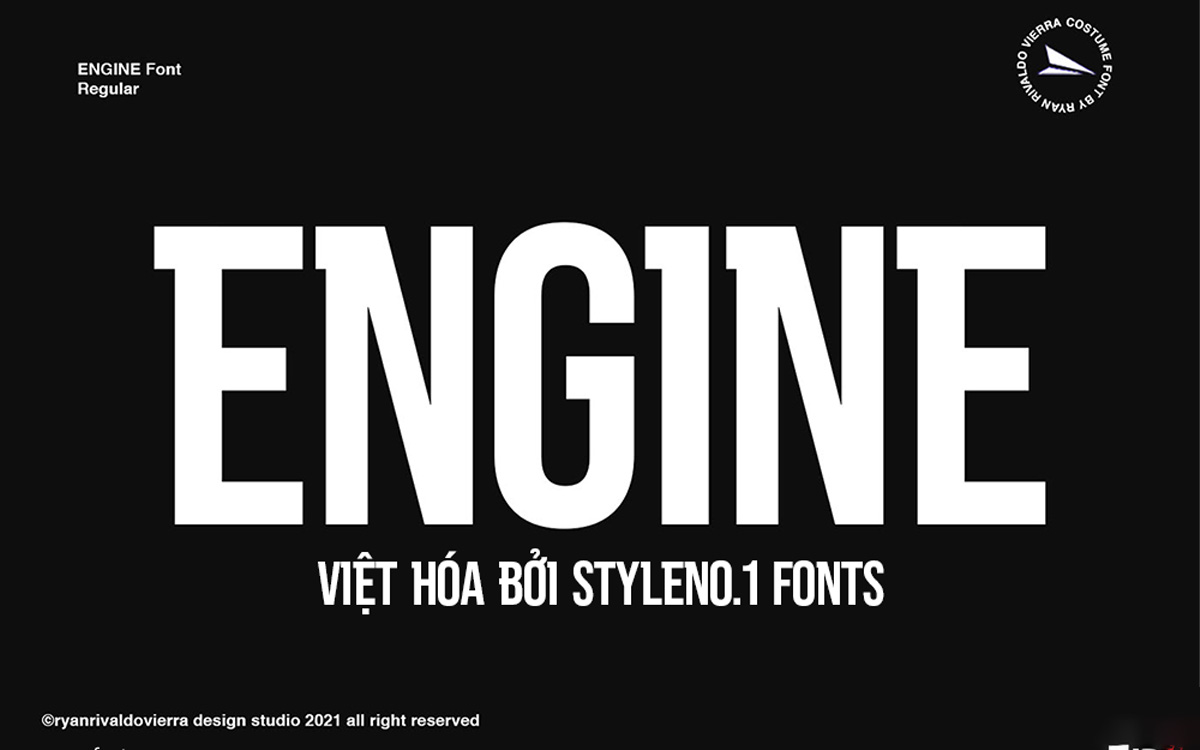
SVN-Engine là bộ font chữ thể thao mang phong cách mạnh mẽ, góc cạnh và hiện đại, được Việt hóa tỉ mỉ dành riêng cho cộng đồng thiết kế đồ họa chuyên nghiệp. Với các nét chữ vuông vức, cấu trúc hình học chắc chắn cùng độ dày ấn tượng, font chữ này thể hiện trọn vẹn tinh thần kỷ luật, sức mạnh và sự bứt phá của các bộ môn gym, fitness cũng như thể thao mạo hiểm. Đây chính là công cụ hoàn hảo giúp các designer kiến tạo nên những ấn phẩm truyền thông thị giác đầy năng lượng và cuốn hút người xem ngay từ cái nhìn đầu tiên.
Font Chữ Cứng, Thể Thao, Gym SVN-Engine – Đột Phá Phong Cách Thiết Kế Đầy Sức Mạnh
Trong ngành thiết kế đồ họa truyền thông, typography (nghệ thuật chữ) không chỉ đơn thuần là phương tiện truyền tải thông tin mà còn là linh hồn tạo nên cảm xúc và thông điệp cho toàn bộ ấn phẩm. Đối với các lĩnh vực đòi hỏi tính hành động cao như thể thao, thể hình, võ thuật hay các chương trình huấn luyện thể chất, việc chọn lựa một kiểu chữ vừa cứng cáp, vừa năng động là yếu tố then chốt quyết định sự thành công của dự án. Font chữ cứng, thể thao, gym SVN-Engine ra đời nhằm đáp ứng chính xác nhu cầu đó, đem lại sự kết hợp hoàn hảo giữa thẩm mỹ đương đại và tính ứng dụng thực tế cao.
1. Đường Nét Góc Cạnh, Cấu Trúc Khỏe Khoắn Và Đậm Tính Kỷ Luật
Điểm đặc trưng nhất của SVN-Engine nằm ở tạo hình chữ nổi bật với các đường nét dày dặn, kết cấu hình học mạch lạc và góc vát sắc sảo. Các chữ cái được dựng trên khung vuông chắc chắn, tạo cảm giác vô cùng kiên định, bền bỉ và giàu sức mạnh – những đặc tính cốt lõi của tinh thần gym và thể thao chuyên nghiệp.
Nhờ cấu trúc nét chữ dày và độ tương phản thị giác lớn, SVN-Engine giúp các tiêu đề (heading) trở nên vô cùng nổi bật, thu hút sự chú ý ngay lập tức dù được đặt trên nền ảnh phức tạp hay các không gian quảng cáo ngoài trời.</p>
2. Bản Việt Hóa SVN Chuẩn Xác, Tối Ưu Kerning Và Dấu Tiếng Việt
Một trong những thách thức lớn nhất khi sử dụng các font chữ thể thao quốc tế là lỗi hiển thị tiếng Việt, khiến các dấu thanh bị lệch, đè chữ hoặc làm mất đi tính cân đối chung. SVN-Engine đã được đội ngũ SVN việt hóa tỉ mỉ, tinh chỉnh khoảng cách ký tự (kerning) và thiết kế lại hệ thống dấu tiếng Việt (sắc, huyền, hỏi, ngã, nặng, các dấu mũ) sao cho hài hòa tuyệt đối với đường nét cứng cáp của bản gốc.
Nhờ vậy, bạn có thể hoàn toàn yên tâm sáng tạo các nội dung tiếng Việt dài hay các câu khẩu hiệu (slogan) mà không lo gặp bất kỳ lỗi font hay mất thẩm mỹ nào trong quá trình dàn trang.
3. Khả Năng Ứng Dụng Đa Dạng Trong Thiết Kế Thương Hiệu Và Truyền Thông
Bản chất linh hoạt và tinh tế trong từng đường nét giúp SVN-Engine dễ dàng thích ứng với hàng loạt các sản phẩm truyền thông thị giác khác nhau. Không chỉ giới hạn trong phòng tập gym, phông chữ này còn phát huy sức mạnh vượt trội trên nhiều lĩnh vực:
- Thiết kế logo & nhận diện thương hiệu: Thích hợp làm logo cho trung tâm Fitness, phòng tập Gym, câu lạc bộ Võ thuật, CrossFit, Boxing, hoặc các đội tuyển thể thao chuyên nghiệp.
- In ấn trang phục thể thao: Rất ưa chuộng khi in số áo, tên cầu thủ, slogan trên áo phông tập gym, áo đấu bóng đá, áo thun thể thao street style.
- Thiết kế Poster & Banner sự kiện: Tạo ấn tượng mạnh mẽ cho các poster giải chạy Marathon, giải đấu Bodybuilding, sự kiện eSports, hay banner khuyến mãi thực phẩm bổ sung.
- Bao bì sản phẩm: Thiết kế nhãn mác cho các dòng thực phẩm bổ sung dinh dưỡng như Whey Protein, Pre-workout, Creatine, nước uống điện giải.
- Ấn phẩm Kỹ thuật số (Digital Media): Làm hình thu nhỏ (thumbnail) YouTube, banner Facebook, highlight Instagram, hiệu ứng chữ trong video TikTok, CapCut, Premiere.
5. Kích Thích Thị Giác Và Tăng Tỷ Lệ Chuyển Đổi Cho Chiến Dịch Marketing
Theo các nghiên cứu về tâm lý học hành vi và thị giác trong thiết kế, những nét chữ dày, vuông vức và góc cạnh có khả năng kích hoạt cảm giác về sự tin cậy, quyết đoán và thúc đẩy hành động mạnh mẽ hơn so với các kiểu chữ mềm mại. Khi ứng dụng SVN-Engine vào các banner quảng cáo, nút kêu gọi hành động (CTA) hay tiêu đề khuyến mãi, thông điệp truyền thông của bạn sẽ mang tính thuyết phục cao hơn, từ đó góp phần gia tăng tương tác và tỷ lệ chuyển đổi cho chiến dịch marketing.
Gợi Ý Bí Quyết Phối Font Và Phối Màu Đẹp Mắt Với SVN-Engine
Để phát huy tối đa sức mạnh thị giác của font chữ cứng, thể thao, gym SVN-Engine, bạn có thể áp dụng một số kinh nghiệm phối hợp thiết kế dưới đây:
1. Phối Hợp Font Chữ (Font Pairing)
Vì SVN-Engine sở hữu cá tính rất mạnh và độ dày cao, bạn nên sử dụng nó làm font tiêu đề chính (Heading). Đối với phần nội dung văn bản chi tiết (Body text), hãy kết hợp cùng các font chữ Sans-serif hiện đại, nét mảnh hoặc trung bình như Roboto, Montserrat, Open Sans hoặc Helvetica để tạo sự cân bằng và giúp người xem dễ đọc hơn.